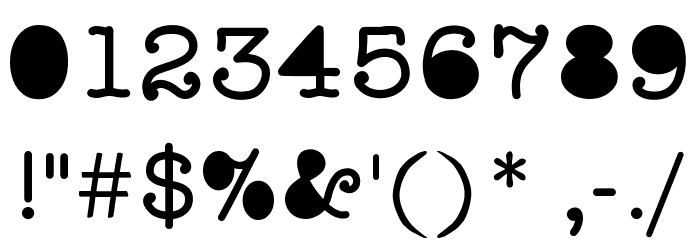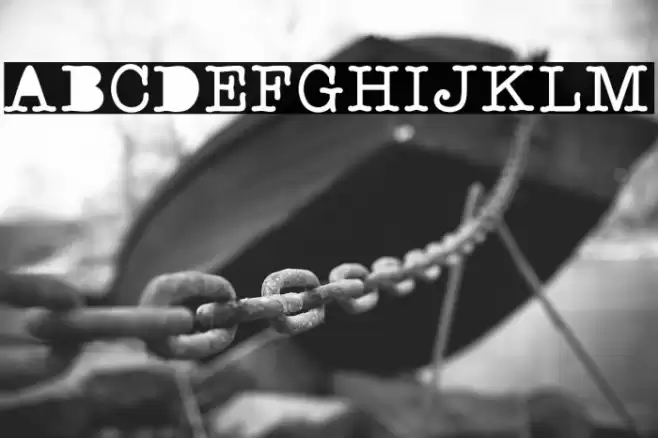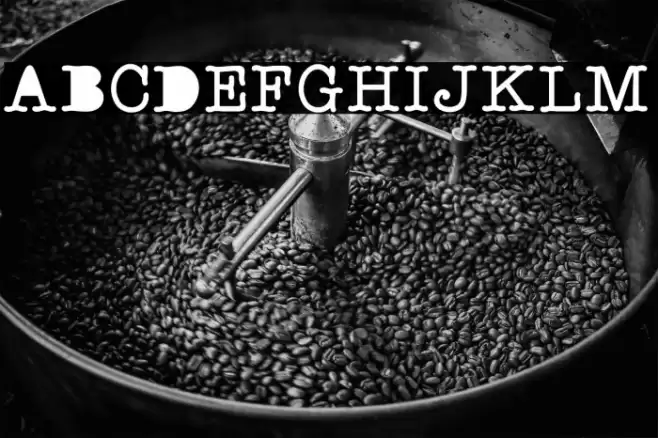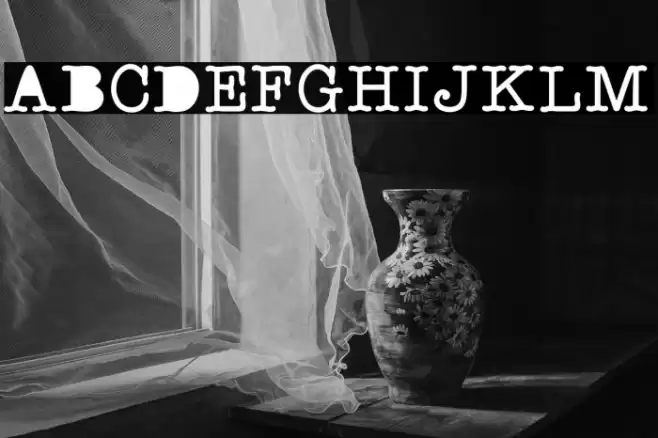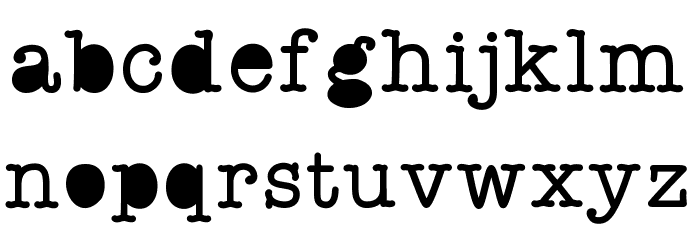
StaffMeeting Font
| Gesamtstil | Playful, Decorative |
| Vorgeschlagene Projekte | Ideal for children's books, playful branding, posters, and creative headlines. |